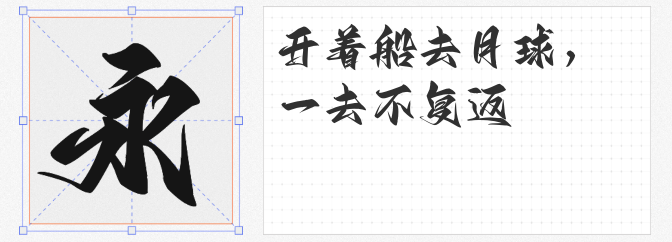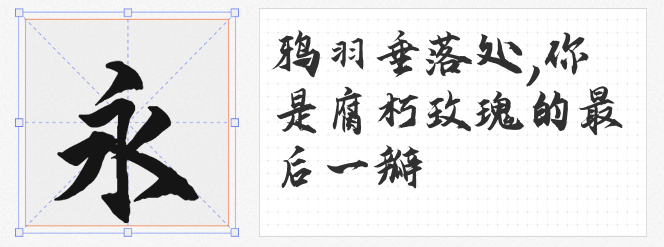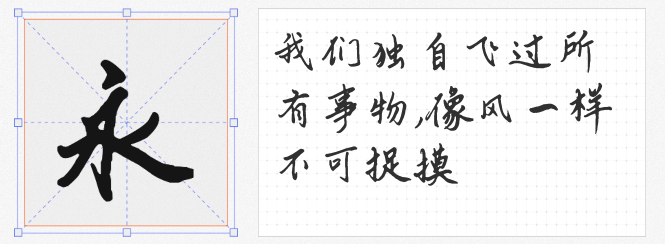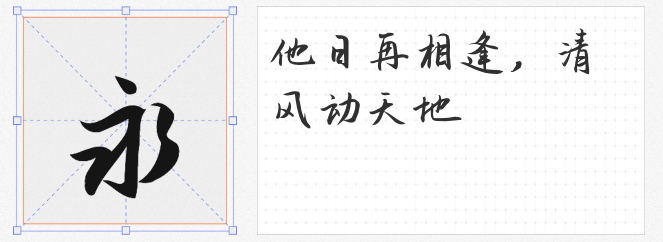
在商业设计中,手写字体以自然灵动的笔触赋予作品温度与个性,而免费商用属性更让创意无惧成本束缚。今日推荐四款风格迥异的潇洒手写字体,它们或如墨舞风云,或似行云流水,为海报标题、品牌包装、影视字幕等场景注入鲜活笔意。
1. 云峰飞云体
这款字体以浓墨重彩的毛笔风格再现书法张力,粗细交错的笔画如云卷云舒,起笔收锋处尽显大气磅礴。其字形结构外松内紧,飞白痕迹与墨迹渗透感模拟真实宣纸效果,尤其适合影视标题、武侠游戏海报等需要震撼视觉的场景,一笔一画皆能传递豪迈气魄。
2. 云峰静龙行书
作为云峰字库首款免费商用行书,它以“稳中带放”为核心特质:笔画端庄而不失灵动,欹侧取势代替绝对平整,复杂笔触被简化为勾挑牵丝,圆转弧线替代生硬折角。这款字体兼具传统行书的韵律感与现代设计的简洁性,适用于书籍封面、文化类海报,在动静之间构建视觉焦点。
3. Aa剑豪体
如其名所示,这款字体以刀刻般的笔触勾勒出武侠世界的快意恩仇。笔画粗犷而不失法度,横竖撇捺间透着洒脱不羁,竖画末端常带出飞溅墨点,仿佛剑客收剑时的凌厉残影。它特别适合运动品牌、国潮服饰及游戏界面设计,用笔墨的张力诠释“破局而出”的叛逆精神。
4. 千图笔锋手写体
不同于前三者的刚劲,这款字体以柔和弧线重塑手写美学。笔画间通过连笔一气呵成,转折处圆润如新月,字形虽简洁却暗藏节奏变化,如清风拂过留白的诗笺。其清新气质适配文艺活动海报、独立杂志封面或手账贴纸,在轻盈笔触中传递治愈感。
四款字体虽皆为手写风格,但通过笔触粗细、连笔方式与结构松紧的差异,可满足从豪放到婉约的多元需求。设计师不妨将其纳入字体库,让每个项目都能找到“笔墨相生”的完美搭档。